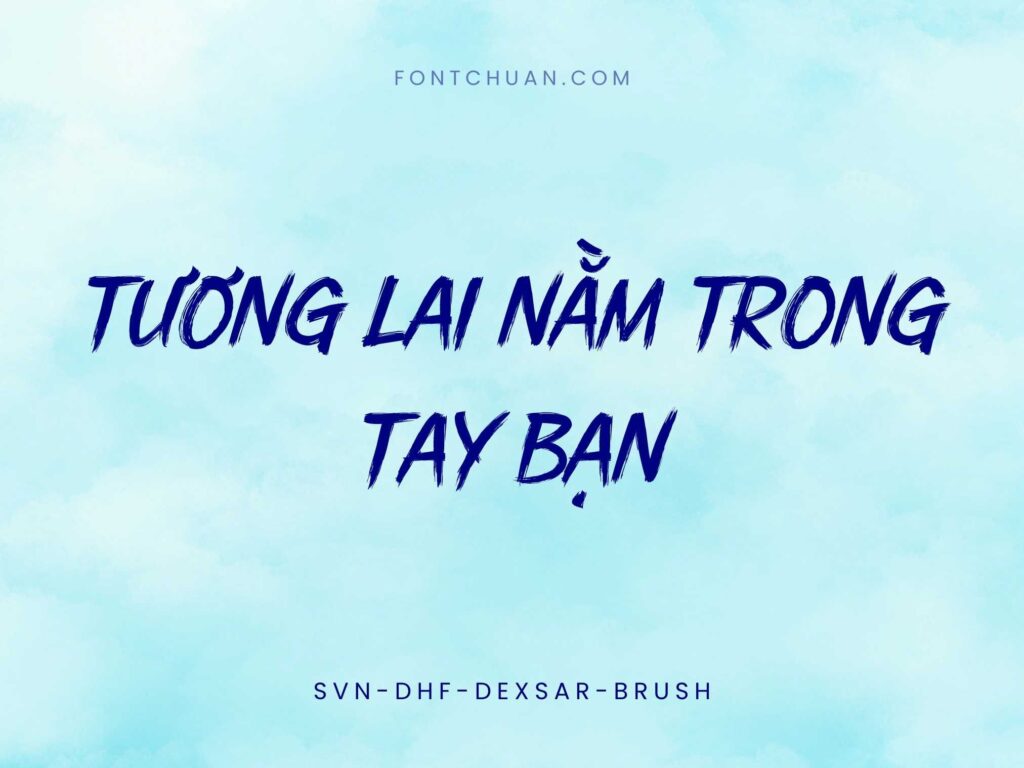
Font SVN Dexsar Brush Việt Hóa
Dexsar Brush là một font chữ brush chi tiết cao, được thiết kế bởi Dharmas Studio. Font này bao gồm hơn 240 ký tự và được trang bị các tính năng OpenType, cho phép tạo cảm giác tùy chỉnh cho thiết kế của bạn. Font đã được Việt hóa để hỗ trợ tiếng Việt bởi Styleno.1 Fonts, đồng thời hỗ trợ nhiều ngôn ngữ khác, giúp mở rộng phạm vi sử dụng trên toàn cầu. Font này được chia sẻ miễn phí cho mọi mục đích sử dụng trên trang Styleno.1 Fonts, đáp ứng nhu cầu của người dùng và ứng dụng thực tế vào các dự án thiết kế.
Đặc điểm thiết kế của Dexsar Brush bao gồm các nét cọ mạnh mẽ và tự nhiên, tạo cảm giác năng động và sáng tạo. Font này phù hợp cho các ứng dụng như tiêu đề, logo, đồ họa trò chơi và các dự án sáng tạo khác. Các ngành nghề phù hợp bao gồm quảng cáo, nghệ thuật và thiết kế đồ họa.